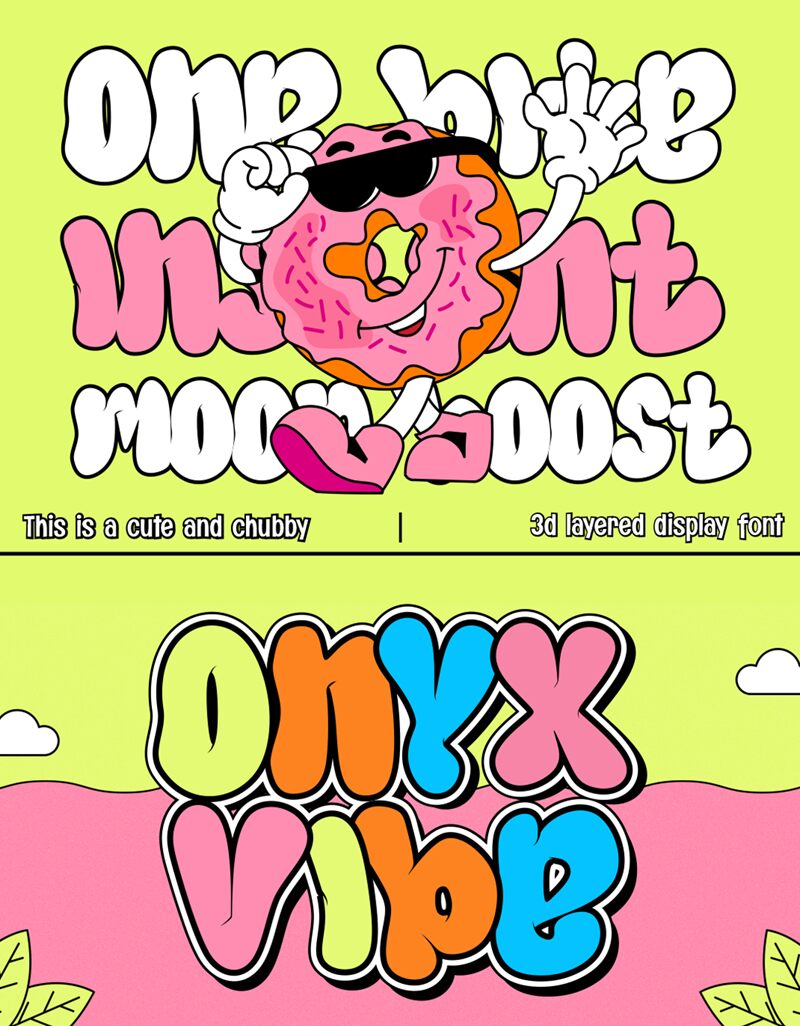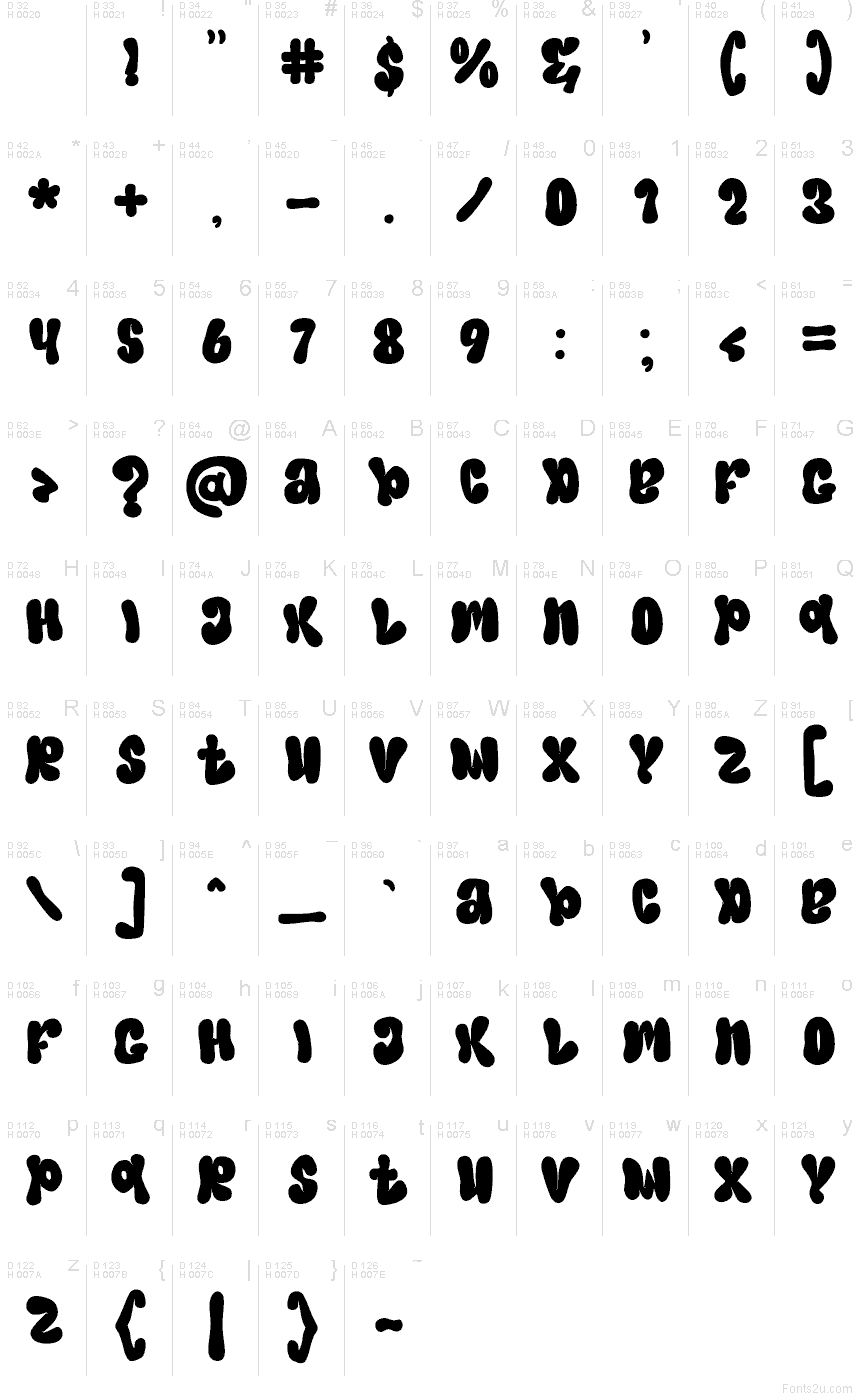
Onyx Vibe Solid
Il font Onyx Vibe Solid di Muhammad Panji Ramdhani di Sipanji x Figuree irrompe sulla scena con lettere in stile graffiti corpose e intrise d'inchiostro, che ricordano il tratto fluido di un pennarello a punta larga. La famiglia Onyx Vibe mantiene forme morbide e dinamiche, con una spaziatura naturale e profili audaci che restano leggibili anche a grandi dimensioni. È un font graffiti gratuito che punta tutto su un'attitudine giocosa senza risultare mai disordinato.
Usa Onyx Vibe Solid per dare un'energia immediata a grafiche streetwear, poster per lo skate, flyer musicali, miniature YouTube, set di adesivi, titoli per eventi e loghi dal segno incisivo. Questo font gratuito brilla anche sulle confezioni quando cerchi quel tocco manuale che mantiene una stampa nitida. Abbinalo a un sans serif semplice e stretto per i testi più piccoli e dai spazio a Onyx Vibe Solid: le parole brevi in grandi formati appaiono particolarmente nitide e decise.